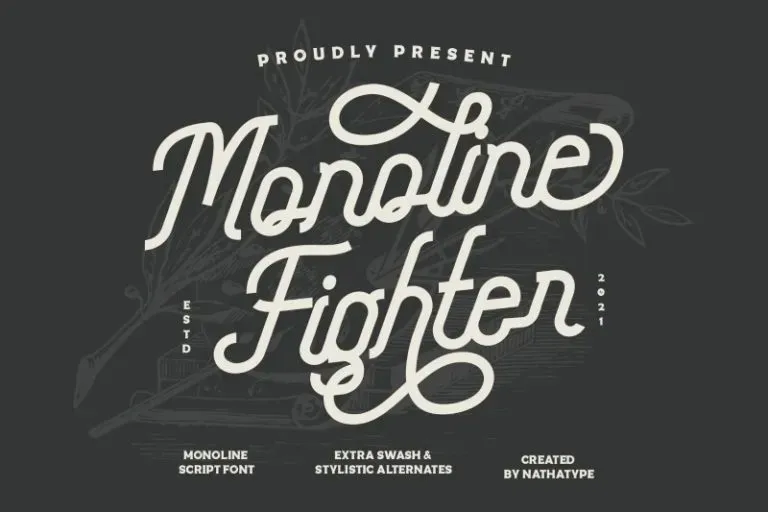
Monoline Fighter Font – Download Grátis
Esta é uma fonte script monoline desenvolvida pelo Din Studio. Ela mantém seus influentes traços do calligrafico ao mesmo tempo contemporânea e atual. A fonte foi pensada cuidadosamente para se misturar facilmente em suas criações. É uma escolha excelente para adicionar um certo nível de elegância junto com um toque vintage. Esta font customizada foi projetada especificamente para atender a qualquer necessidade que você possa ter. Perfeita tanto para posts e anúncios no Facebook, design de citações impressas ou estampas em tênis, embalagens, até mesmo como overlay de texto moderno sobre uma imagem de fundo. Seja para o seu negócio ou trabalho pessoal, esta font é perfeitamente adaptável às suas necessidades e vai enriquecer o visual do seu projeto de design.